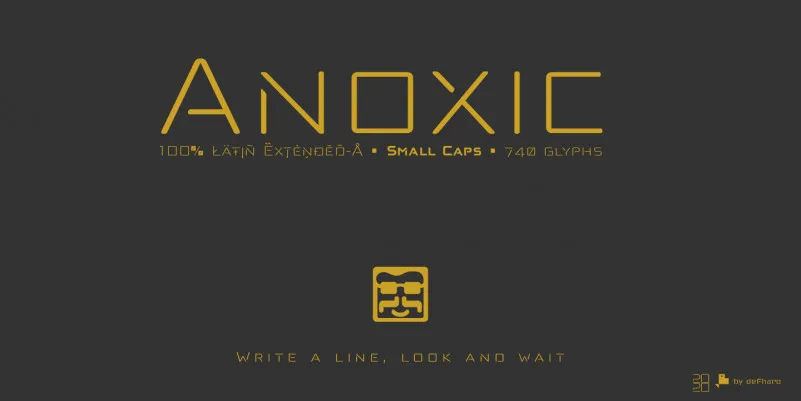
Anoxic Font Family – Fonte Grátis
Anoxic Font Family
Anoxic Font Family é uma família de tipo semi-stencil com acabamento arredondado que oferece muitas opções para personalizar seu design. Com 16 estilos distribuídos entre quatro famílias principais – Roman, Small Caps, Outline & Oblique e Obliqula, a fonte inclui letras menores, 9 conjuntos de números e três letras maiúsculas. Além disso, a família destaca-se por sua versatilidade, oferecendo funções abertas avançadas para um uso mais refinado. Este tipo de fonte é perfeito para quem busca uma solução estilosa e moderna, capaz de dar um toque único a qualquer projeto. Desenvolvida pelo designer defharo, Anoxic não apenas adiciona um novo ícone à sua coleção de tipos digitais, mas oferece recursos únicos que permitem criar design gráfico mais complexo e sofisticado.